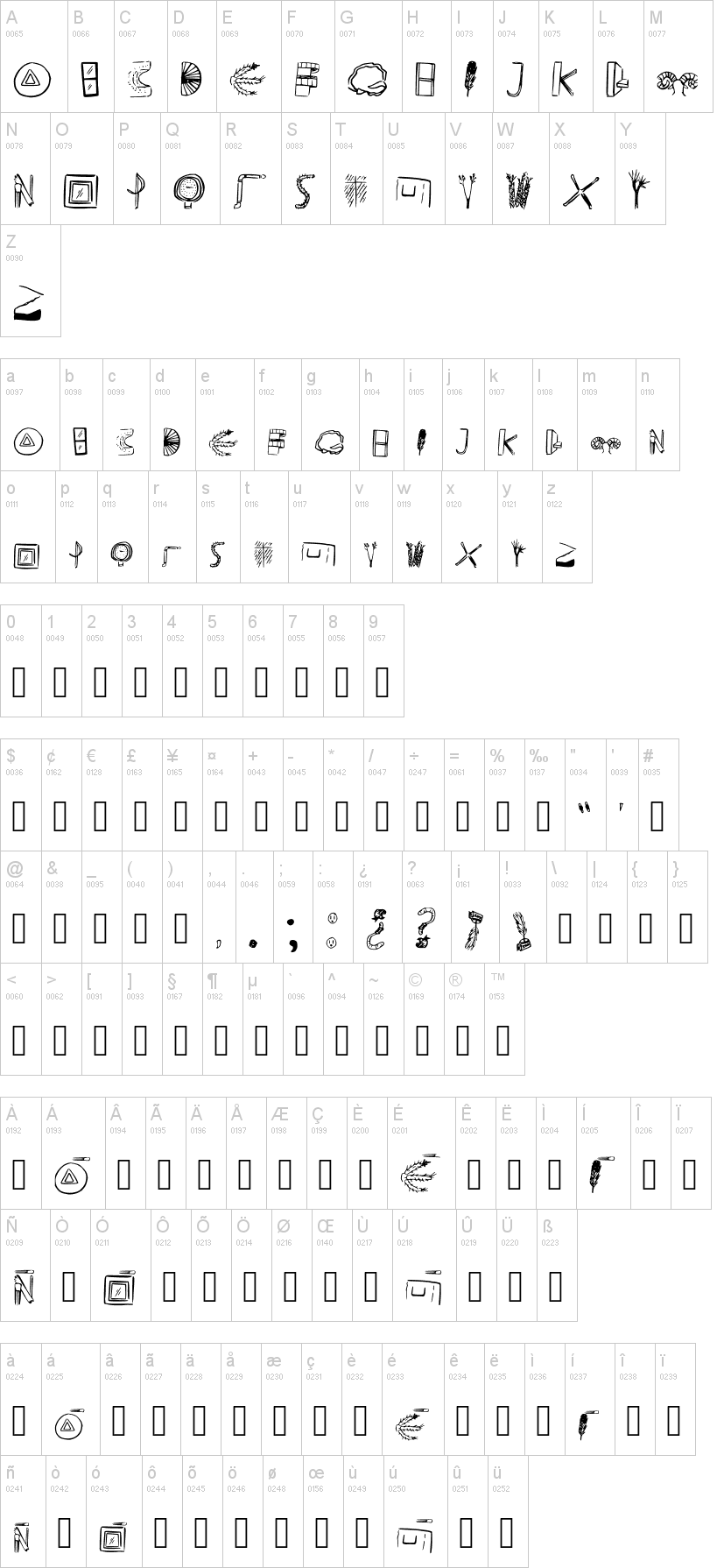
Note of the authorEste fue un ejercicio de la licenciatura en Artes Plásticas, pero lo llevé un paso más allá del papel y la convertí en una tipografía propia. El ejercicio consistía en tomar fotos de objetos en el campus universitario y encontrar formas que se asimilaran a las letras del abecedario, luego se procedió a dibujar las formas para crear tipografías únicas sobre papel. Por gusto y viendo el potencial, decidí convertirla en una tipografía funcional.